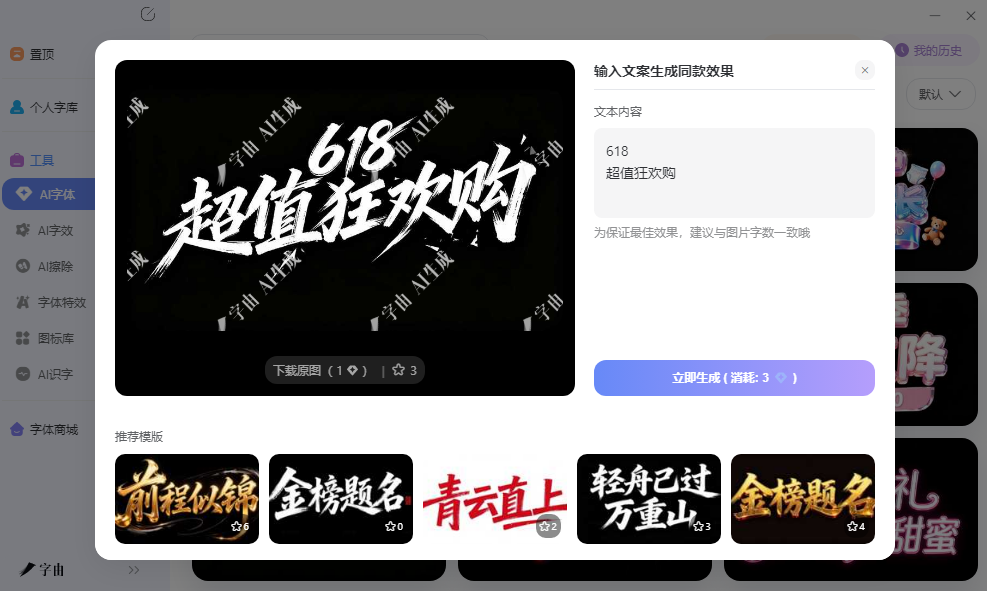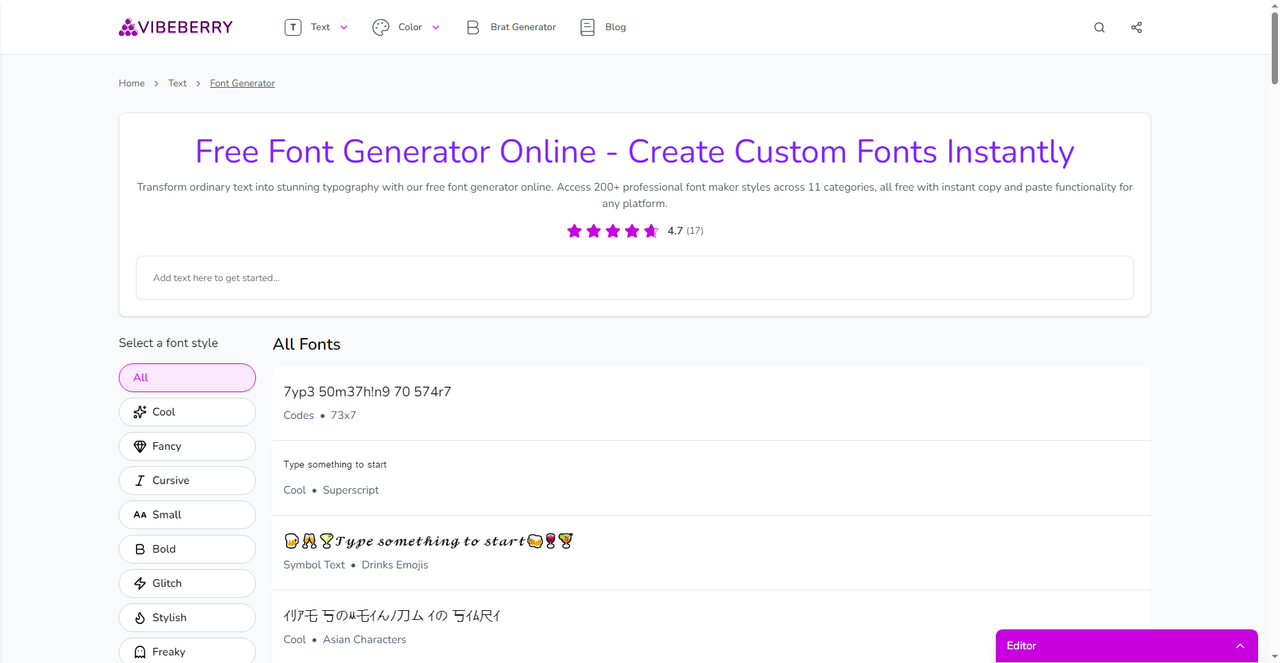
字体设计在线生成方案,不会做设计也能出好看效果
很多人想做一张带设计感标题的图片,但打开Photoshop就被复杂的图层样式劝退。调投影角度、渐变节点、描边宽度,参数之间互相影响,改一个值可能整个效果就崩了。其实现在有不少字体设计在线生成工具可以直接出图,输入文案就能拿到带特效的透明背景图片,拖进PPT、海报或者公众号封面里就能用。这篇文章整理的五个平台,从中文AI渲染到英文装饰字体都有包括。
字由的AI字体功能对没有设计基础的人比较友好。它不需要你懂图层样式,也不需要会调参数,操作方式是在网页上选择模板、输入文案、点击生成,三步完成。生成速度比较快,大约二十多秒就能拿到成品。导出格式是PNG,默认透明背景,这意味着可以直接叠加在PPT背景、海报底图或者社交媒体模板上,不需要抠图。对于临时需要做一张活动海报或者公众号封面的人来说,这种即拿即用的方式比从零开始学设计软件要现实得多。图片质量足够应付屏幕显示和一般印刷需求,分辨率在常规尺寸下不会出现模糊。
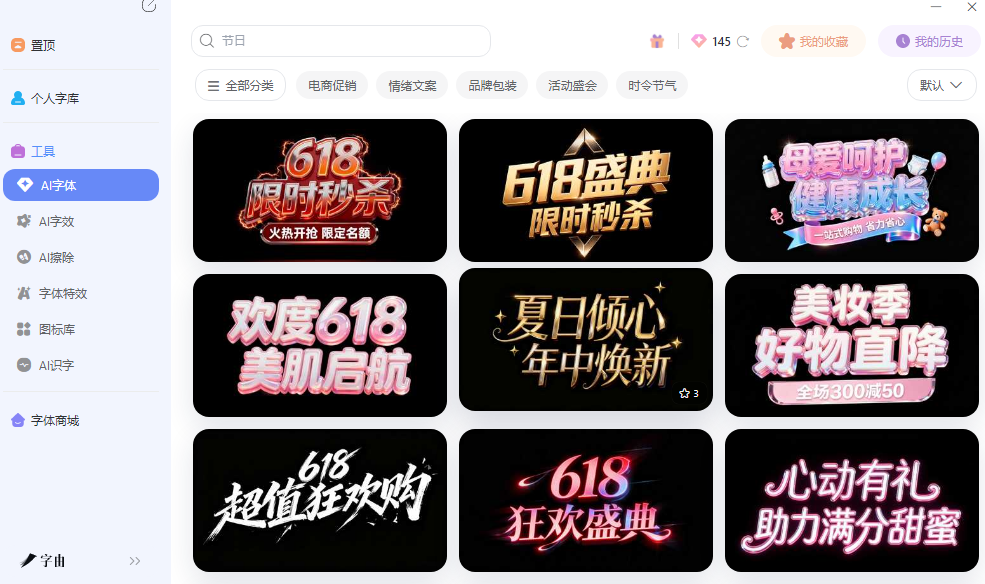
需要调整效果时,可以换一款模板重新生成。预览区支持输入自己的文案查看效果,确定合适再点击正式生成,避免了消耗算力点试错。这个细节对免费用户比较友好,预览不消耗额度,只有正式生成才扣点。
2、VibeBerry
VibeBerry是一个免费在线字体生成器,目前收录了超过两百种风格。网站支持多平台使用,生成的文字可以在Instagram、Twitter、TikTok等社交媒体上直接显示。风格偏向现代和年轻化,很多适合做个人简介、帖子标题或者故事封面。
操作上输入文字后选择风格,复制生成的特殊字符即可使用。作为字体设计在线生成的渠道,VibeBerry的优势在于风格更新快,紧跟社交媒体的设计趋势,适合需要频繁更新视觉风格的个人用户或者新媒体运营者。网站上还会标注每种风格适合的平台,帮助用户快速找到在特定社交媒体上显示效果最好的字体。
3、Fontgenerators
Fontgenerators 的文本艺术字体生成器偏向复古风格,包括打字机效果、ASCII艺术、老式印刷体等。输入文字后,系统会实时转换为对应的复古风格,效果比较独特。这种风格在常规渠道不太容易找到,适合做怀旧主题的海报、复古风格的社交媒体内容或者文创设计。
网站上还提供了多种参数调节选项,可以微调效果的强度和细节。作为字体设计在线生成的补充渠道,Fontgenerators 在复古和文本艺术这个细分领域有一定特色,适合需要差异化视觉效果的项目。生成的结果可以直接复制为文本或者保存为图片,两种格式都支持,使用场景比较灵活。
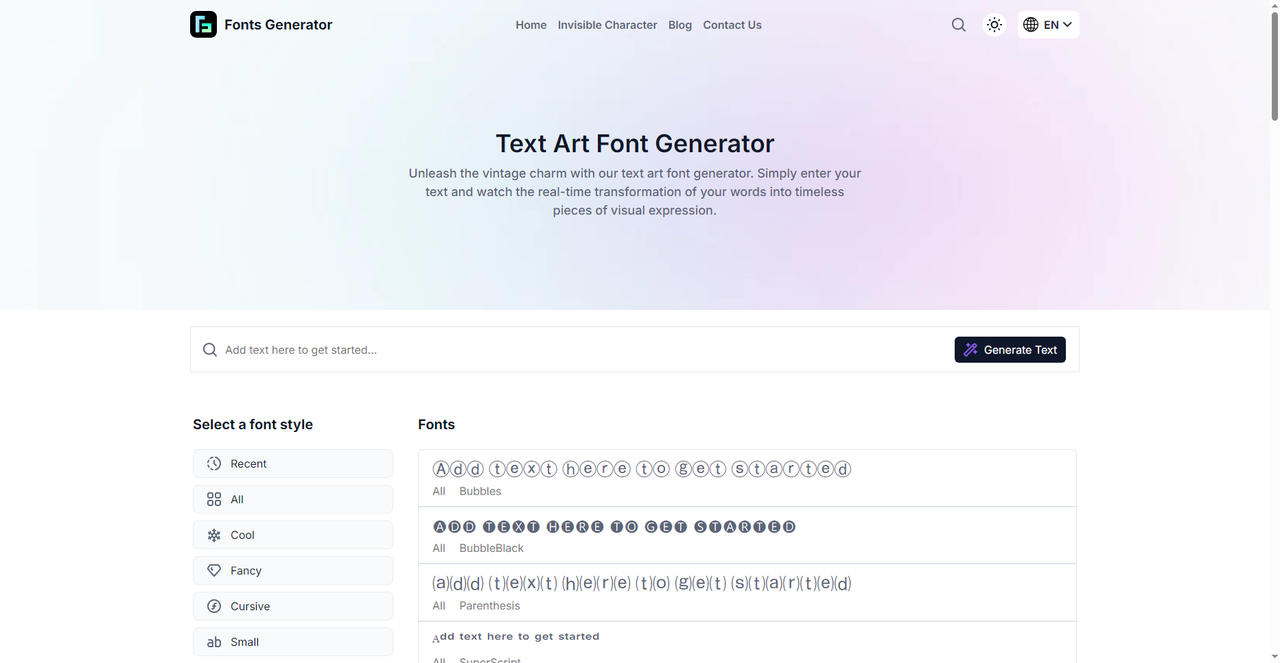
4、Fontgenerators
Fontgenerators.net的文本艺术字体生成器偏向复古风格,包括打字机效果、ASCII艺术、老式印刷体等。输入文字后,系统会实时转换为对应的复古风格,效果比较独特。这种风格在常规渠道不太容易找到,适合做怀旧主题的海报、复古风格的社交媒体内容或者文创设计。
网站上还提供了多种参数调节选项,可以微调效果的强度和细节。作为字体设计在线生成的补充渠道,Fontgenerators.net在复古和文本艺术这个细分领域有一定特色,适合需要差异化视觉效果的项目。生成的结果可以直接复制为文本或者保存为图片,两种格式都支持,使用场景比较灵活。
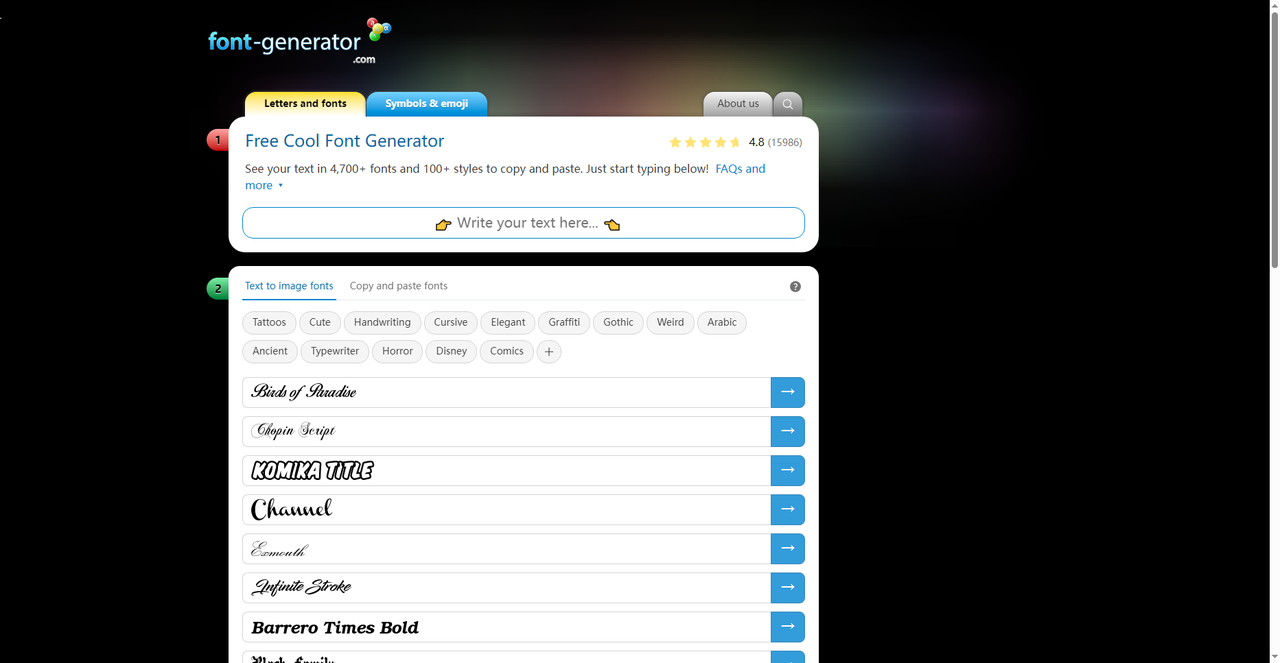
5、ArtFonts.online
ArtFonts.online是一个在线艺术字体生成器,界面比较简洁。输入文字后,系统会自动转换为多种美化字体样式,包括花体、粗体、手写体等装饰性变体。这些变体基于Unicode字符集,可以直接复制粘贴到社交媒体、聊天软件或者文档中使用。和字由生成图片的方式不同,ArtFonts.online产出的是文本字符,可以在任何支持Unicode的平台上显示,后续需要修改文字内容时直接编辑即可,不需要重新生成。
对于需要字体设计在线生成、但又想要可编辑文字的用户来说,这种方式比较灵活。网站上还提供了多种预设风格,点击即可切换,不需要手动调参数。生成的特殊字符在Instagram、Twitter、Facebook等平台上都能正常显示,适合用来做个人简介、帖子标题或者评论区的装饰文字。
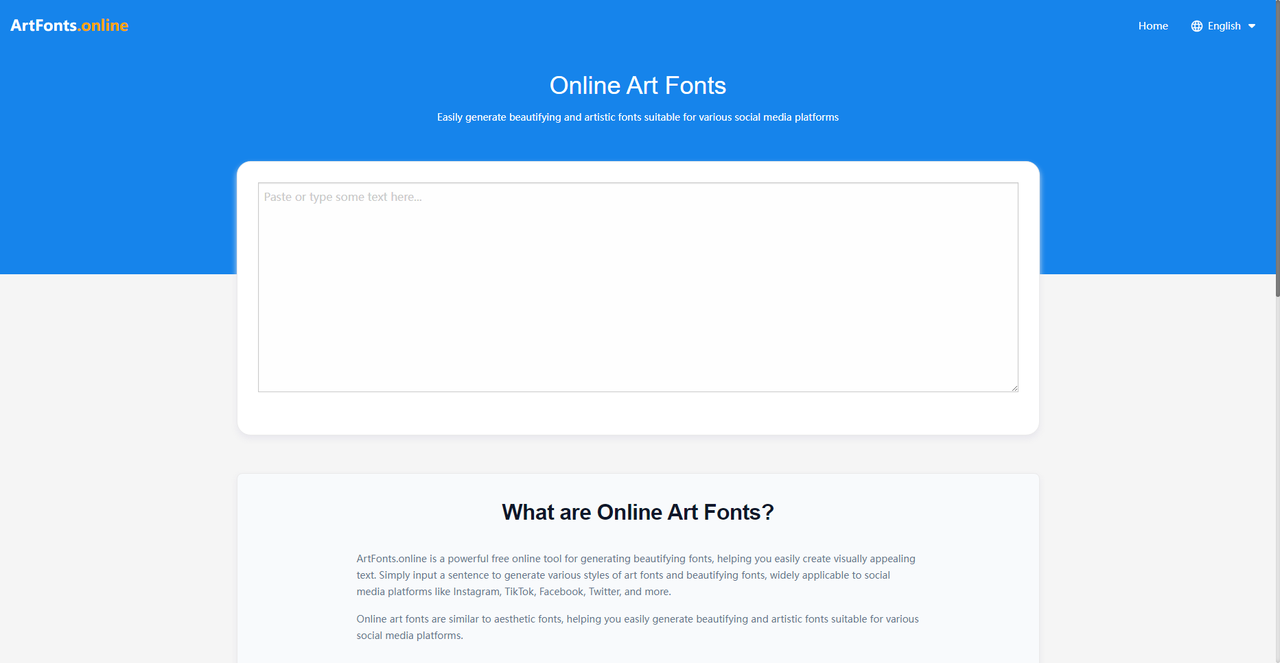
这样看来,不需要会Photoshop也能做出带设计感的标题字,字由的AI字体在中文场景下生成速度快、风格选择多,配合每日免费额度,作为字体设计在线生成的主力渠道比较省心。ArtFonts.online和VibeBerry产出的是可编辑字符,适合社交媒体直接使用。Font-generator的样式数量大,适合批量探索。Fontgenerators的复古风格在差异化项目中比较出彩。